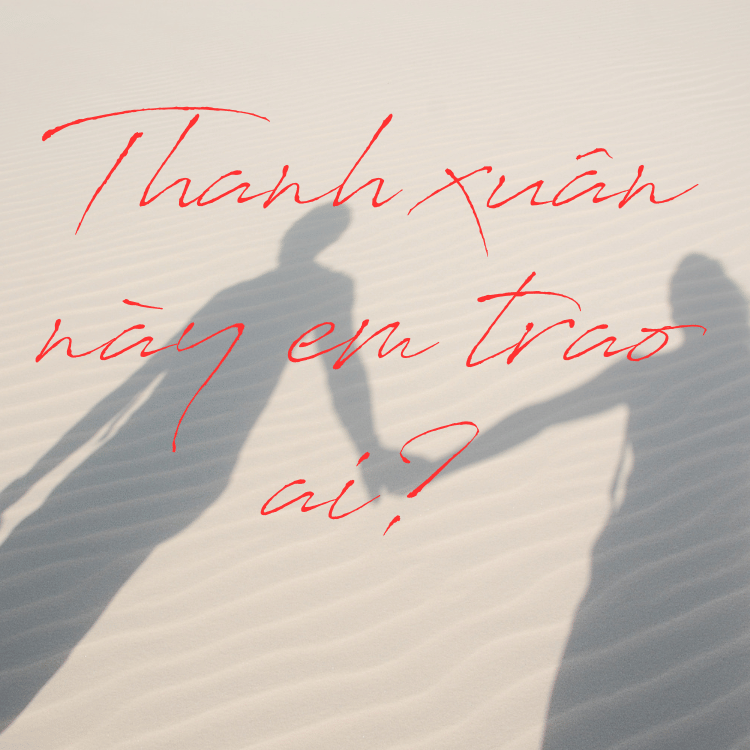
Font việt hoá MTD Antro Vectra
Font việt hoá MTD Antro Vectra – Bộ Font Chữ Ký Sang Trọng Cho Thiết Kế
Giới thiệu về Font việt hoá MTD Antro Vectra
Trong thế giới đồ họa hiện đại, việc tìm kiếm một mẫu Font Miễn Phí mang phong cách handwriting cá tính luôn là ưu tiên hàng đầu của các nhà thiết kế. Font việt hoá MTD Antro Vectra nổi lên như một lựa chọn hoàn hảo nhờ những đường nét thanh mảnh, bay bổng nhưng không kém phần chuyên nghiệp. Đây là bộ phông chữ được tối ưu hóa tiếng Việt, giúp người dùng dễ dàng ứng dụng vào các phần mềm thiết kế mà không lo lỗi dấu hay khoảng cách chữ.
Đặc điểm nổi bật của bộ font chữ ký độc đáo
Thiết kế mềm mại và tự nhiên
Font việt hoá MTD Antro Vectra mô phỏng chân thực nét bút tay thủ công, tạo cảm giác gần gũi và chân thực cho tác phẩm. Các đường nét nối giữa những ký tự được xử lý tinh tế, mang lại vẻ ngoài thanh thoát giống như một chữ ký cá nhân thực thụ. Điều này giúp bộ font cực kỳ phù hợp cho việc thiết kế logo thương hiệu cá nhân, thiệp mời đám cưới hay các hình ảnh trích dẫn đầy cảm hứng trên mạng xã hội.
Ứng dụng đa dạng trong học tập và công việc
Đối với học sinh và sinh viên, bộ font này là công cụ đắc lực để trang trí bìa tiểu luận, làm thiệp tặng thầy cô hay tạo ra những slide thuyết trình ấn tượng. Tính thẩm mỹ cao giúp thông điệp truyền tải trở nên cuốn hút và có chiều sâu hơn. Sự kết hợp giữa nghệ thuật viết tay và sự chính xác của font kỹ thuật số đã tạo nên sức hút khó cưỡng cho sản phẩm này.
Để đạt hiệu quả thị giác tốt nhất, bạn nên kết hợp Font việt hoá MTD Antro Vectra với các phông chữ không chân (Sans Serif) đơn giản. Sự đối lập này sẽ làm nổi bật nét mềm mại của bộ font chữ ký. Hãy tải ngay tại Font Miễn Phí, Font Việt Hóa, Font việt hoá MTD Antro Vectra để trải nghiệm sự sáng tạo không giới hạn. Đây chắc chắn là bộ sưu tập không thể thiếu cho bất kỳ ai yêu thích cái đẹp và sự tinh tế trong từng nét chữ Việt.